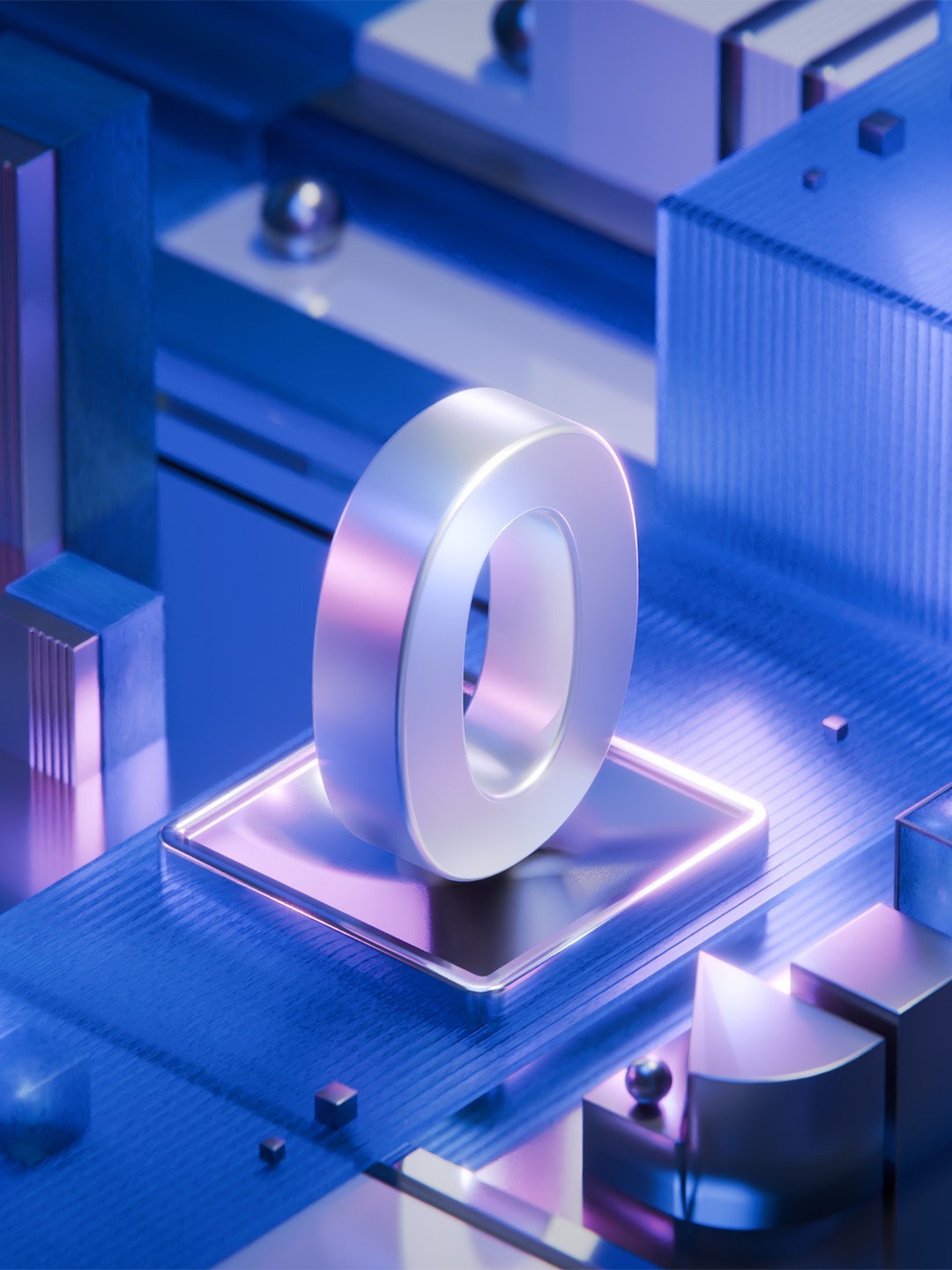
VTB OMEGA: Визуальное исследование шрифтовой экосистемыПроект переосмысляет цифровую идентичность ВТБ через новый шрифт Omega, созданный с Paratype.Задача: Создать бренд-фильм о технологичности, масштабе и системности банка.Концепция: Абстрактная цифровая среда, где типографика — главный элемент архитектуры.Стек: Design & Art Direction (айдентика), 3D Production (моделирование, процедурные текстуры, свет